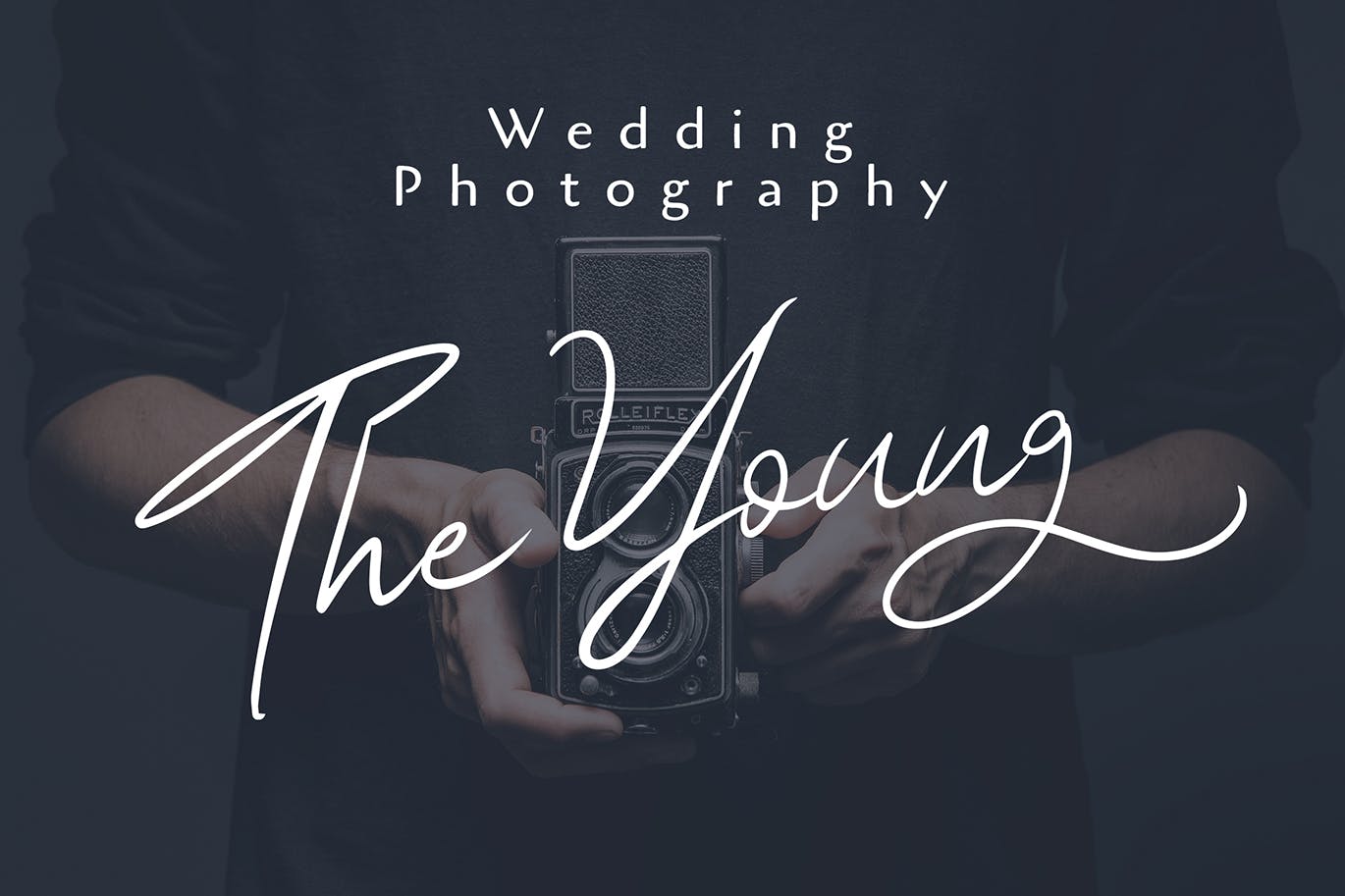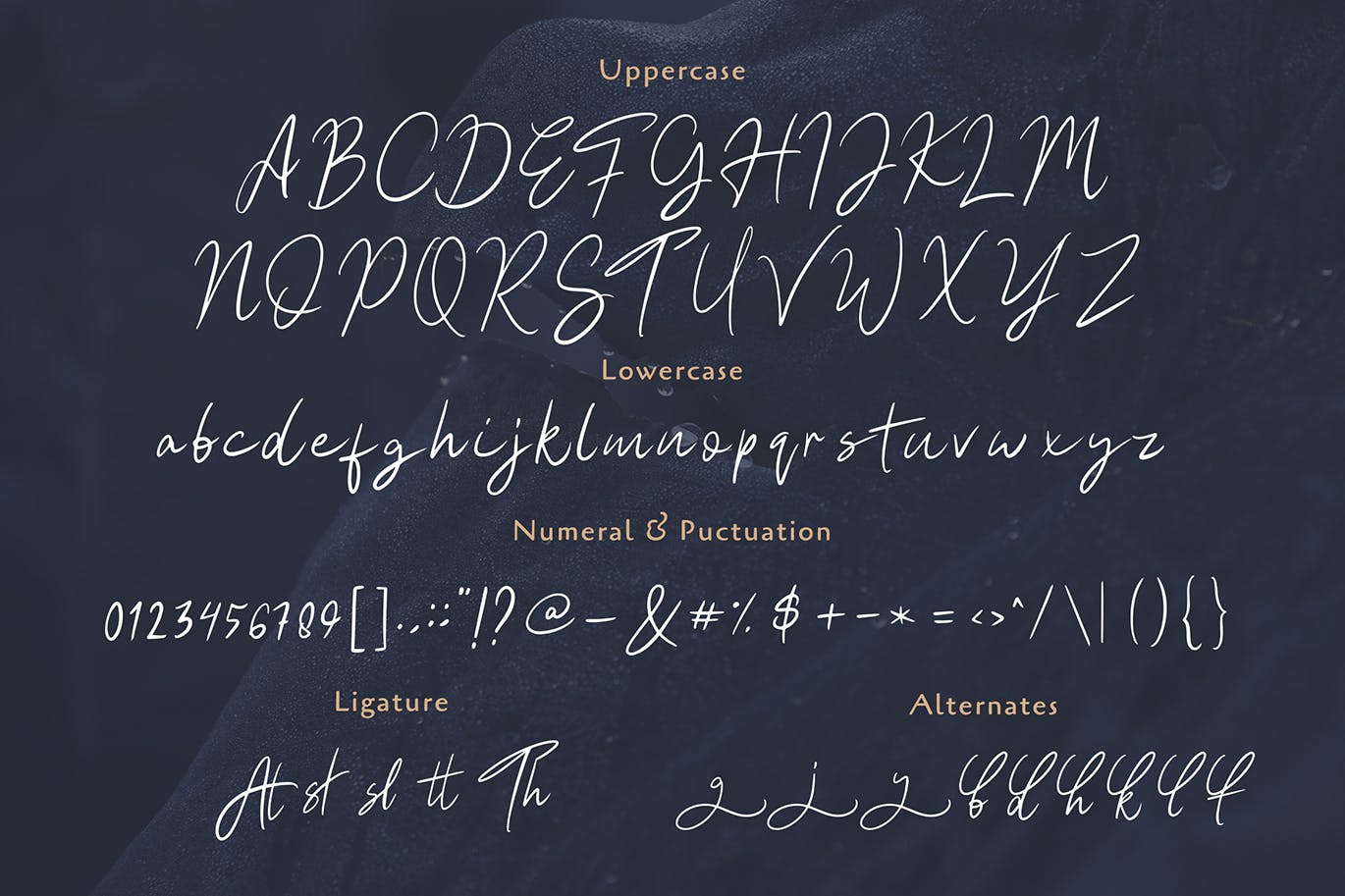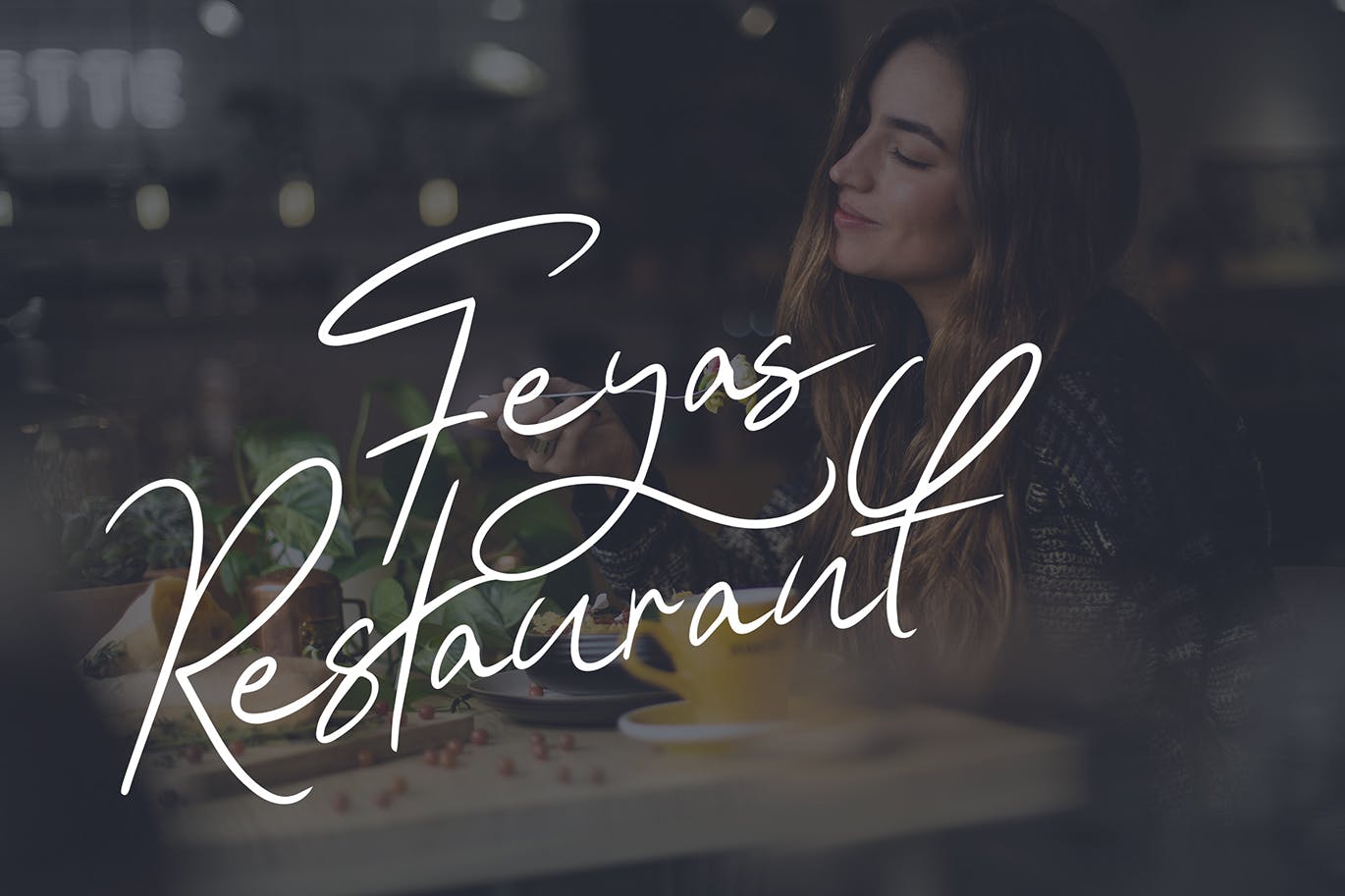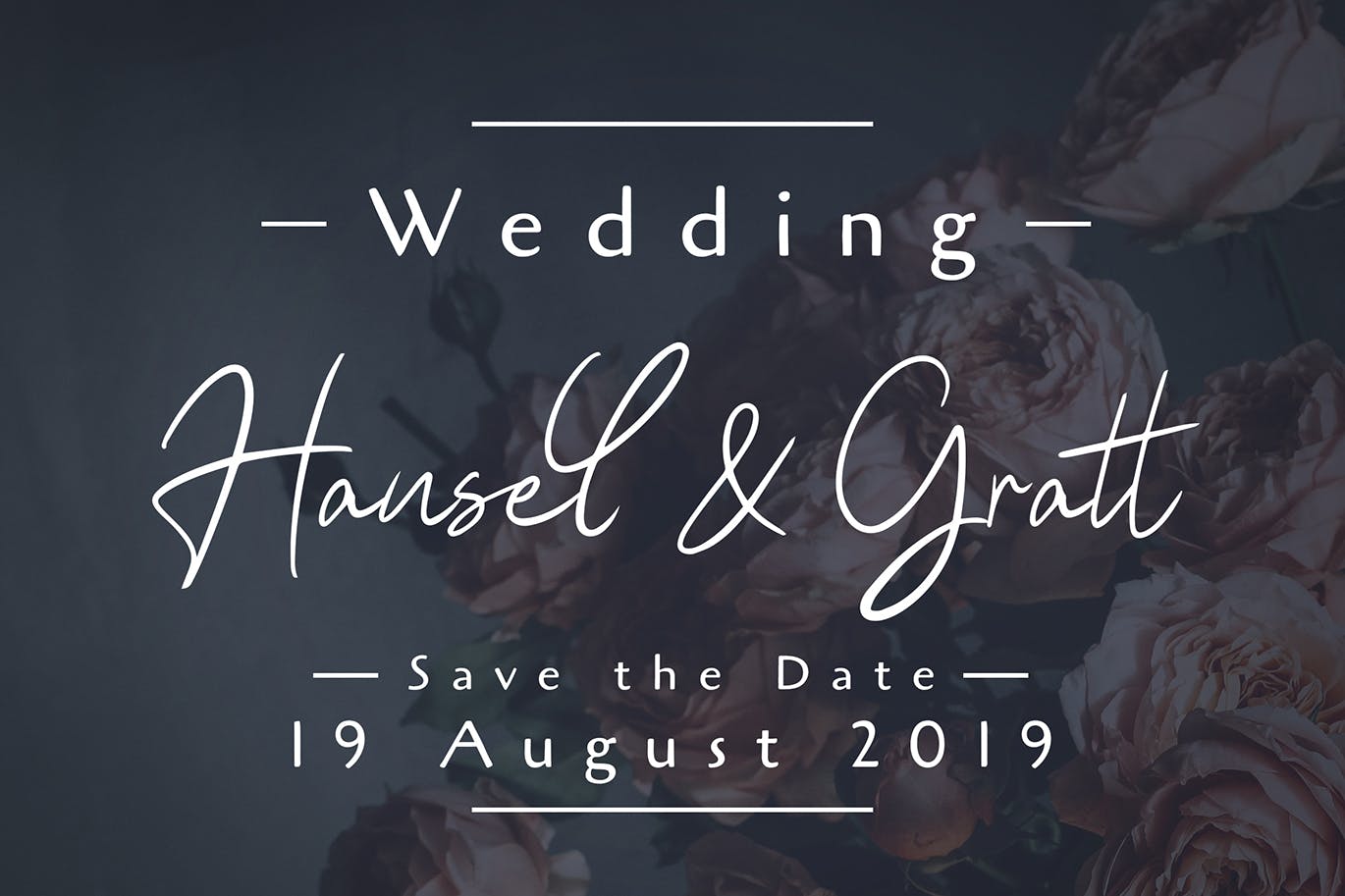
Hesgaki - فونت امضای لوکس
این فونت زیبا برای دعوتنامهها، کارتهای تبریک، مواد برندینگ، کارتهای کسبوکار، نقلقولها، پوسترها و بسیاری موارد دیگر بسیار مناسب است!